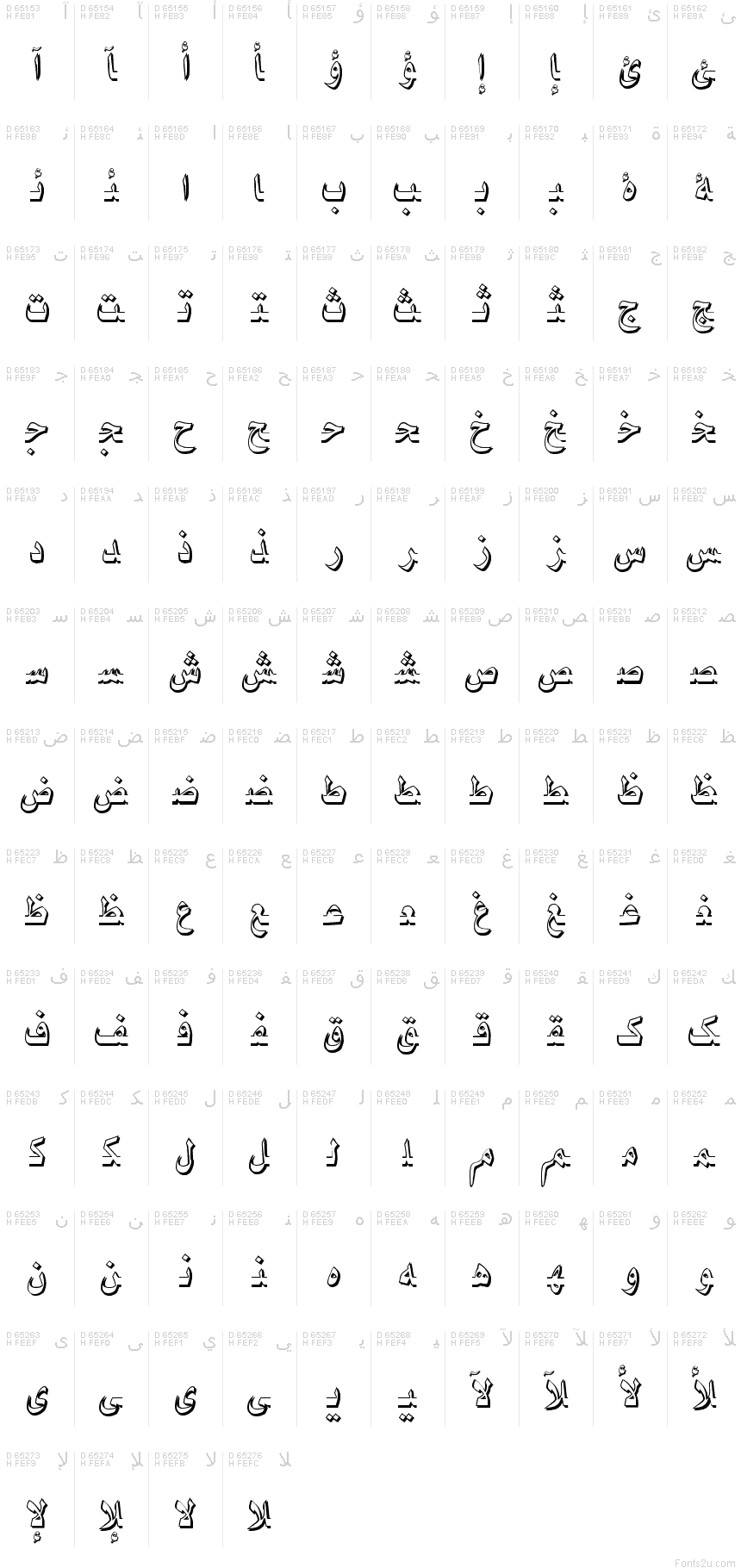
B Niki Shadow od Borna Rayaneh je bezplatné arabské titulkové písmo s masívnym, tieňovaným vzhľadom, ktorý vychádza z dizajnu novinových titulkov. Písmená pôsobia ako výrazné, kompaktné tvary s efektom odsadeného tieňa. Celkový dojem je preto skôr plagátový než kaligrafický, pričom hlavnú úlohu zohrávajú tmavé siluety.
Vďaka tomu je ideálnou voľbou pre hudobné letáky, nápisy na prevádzkach, obaly, titulky v časopisoch a krátke textové karty, kde toto bezplatné písmo potrebuje okamžitú vizuálnu váhu. Skvele funguje aj pri logách alebo krátkych brandingových nápisoch, pretože vstavaný tieň dodáva literám hotový, vrstvený vzhľad bez potreby ďalších úprav.